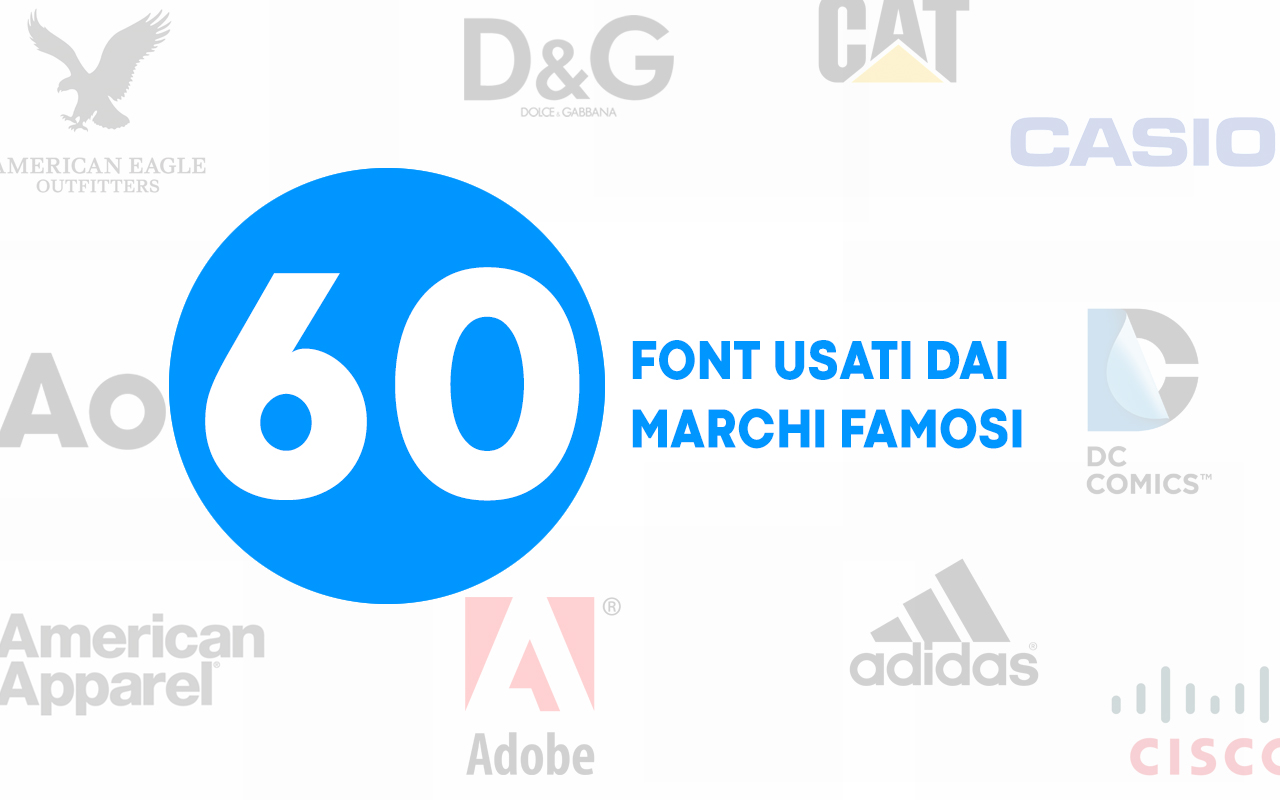
i font utilizzati nei loghi famosi e dove scaricarli
Hai sempre voluto conoscere i nomi dei caratteri utilizzati nei loghi di marchi famosi e conosciutissimi come Adidas, Calvin Klein, FedEx, Gillette, Jaguar, Lufthansa, Omega, Rolls-Royce, Visa, ecc. ? Si? Bene! Abbiamo compilato un elenco in ordine alfabetico di 60 loghi noti con i relativi font usati e i collegamenti al download.
In alcuni casi, i caratteri sono stati modificati dal originale per creare un marchio personalizzato per i singoli marchi oppure sono stati creati ad hoc per il cliente, In questo caso, abbiamo elencato il carattere più vicino possibile che corrisponde al logo.
1. Adidas
Adidas logo font - Avant Garde Gothic Demi
Avant Garde Gothic Demi
2. Adobe
Adobe logo font - Myriad Pro Bold Condensed
Myriad Pro Bold Condensed
3. American Apparel
American Apparel logo font - Helvetica Black
Helvetica Black
4. American Eagle
American Eagle logo font - Garamond / Newburgh
Garamond / Newburgh
5. AOL
AOL logo font - Avenir Next Pro Bold
Avenir Next Pro Bold
6. Aston Martin
Aston Martin logo font - Optima Roman
Optima Roman
7. BBC
BBC logo font- Gill Sans Std
Gill Sans Std
8. Black & Decker
Black & Decker logo font - Avenir Black
Avenir Black
9. Calvin Klein
Calvin Klein logo font - Avant Garde Gothic
Avant Garde Gothic
10. Casio
Casio logo font - Eurostile Ext Black
Eurostile Ext Black
11. Caterpillar
Caterpillar logo font - Helvetica Inserat Roman
Helvetica Inserat Roman
12. Cisco
Cisco logo font - Futura Bold
Futura Bold
13. Dolce & Gabbana
Dolce & Gabbana logo font - Futura Demi Bold
Futura Demi Bold
14. DC Comics
DC Comics logo font - Gotham Bold
Gotham Bold
15. eBay
eBay logo font - Univers 53 Extended
Univers 53 Extended
16. ESPN
ESPN logo font- ESP
ESP
17. Facebook
Facebook logo font - Klavika Bold
Klavika Bold
18. FedEx
FedEx logo font - Futura Bold / Univers 67
Futura Bold / Univers 67
19. Fendi
Fendi logo font - Helvetica Bold
Helvetica Bold
20. Flickr
Flickr logo font - Frutiger Black
Frutiger Black
21. Gillette
Gillette logo font - Futura Extra Black Italic
Futura Extra Black Italic
22. Giorgio Armani
Giorgio Armani logo font - Didot
Didot
23. Groupon
Groupon logo font - Avant Garde Gothic Bold
Avant Garde Gothic Bold
24. HTML 5
HTML 5 logo font - Gotham Ultra
Gotham Ultra
25. IBM
IBM logo font - Men In Blue
Men In Blue
26. iTunes
iTunes logo font - Myriad Bold
Myriad Bold
27. Jaguar
Jaguar logo font - Jaguar JC (customized)
Jaguar JC (customized)
28. Jeep
Jeep logo font - Helvetica Bold
Helvetica Bold
29. LG
LG logo font - Helvetica Black
Helvetica Black
30. LinkedIn
LinkedIn logo font - Myriad Bold
Myriad Bold
31. Lufthansa
Lufthansa logo font - Helvetica Bold
Helvetica Bold
32. Mobil
Mobil logo font - Avant Garde Gothic Bold
Avant Garde Gothic Bold
33. NBA
NBA logo font - Helvetica Condensed Black
Helvetica Condensed Black
34. The New York Times
The New York Times logo font - English Towne
English Towne
35. Nutella
Nutella logo font - Avant Garde Gothic Bold
Avant Garde Gothic Bold
36. Omega
Omega logo font - Futura Medium
Futura Medium
37. Panasonic
Panasonic logo font - Helvetica Black
Helvetica Black
38. PayPal
PayPal logo font - Futura Bold Oblique
Futura Bold Oblique
39. PlayStation 3
PlayStation 3 logo font - PhatBoy Slim
PhatBoy Slim
40. Puma
Puma logo font - My Puma
My Puma
41. Rolls-Royce
Rolls-Royce logo font - Myriad Semi Bold
Myriad Semi Bold
42. Snickers
Snickers logo font - Lunch Time Normal
Lunch Time Normal
43. Spotify
Spotify logo font - LL Circular
LL Circular
44. Standard Chartered
Standard Chartered logo font - Helvetica Neue 55 Roman
Helvetica Neue 55 Roman
45. Subway
Subway logo font - Helvetica Black
Helvetica Black
46. Tag Heuer
Tag Heuer logo font - Gill Sans / Humanist
Gill Sans / Humanist 521
47. Target
Target logo font - Helvetica Neue Bold
Helvetica Neue Bold
48. TGI Friday’s
TGI Friday's logo - Gotham Black
Gotham Black
49. Tommy Hilfiger
Tommy Hilfiger logo font - Gill Sans Regular
Gill Sans Regular
50. Toshiba
Toshiba logo font - Eurostile Black
Eurostile Black
51. Toyota
Toyota logo font - Avenir 95 Black
Avenir 95 Black
52. Under Armour
Under Armour logo font - Eurostile Black Extended
Eurostile Black Extended
53. UNICEF
UNICEF logo font - Univers Light
Univers Light
54. USA Today
USA Today logo font - Futura Bold
Futura Bold
55. Visa
Visa logo font - Myriad Black Italic
Myriad Black Italic
56. Vogue
Vogue logo font - Didot
Didot
57. Walmart
Walmart logo font - Myriad Pro Bold
Myriad Pro Bold
58. Walt Disney
Walt Disney logo font - Walt Disney Script
Walt Disney Script
59. WhatsApp
WhatsApp logo font - Helvetica Neue 75 Bold
Helvetica Neue 75 Bold
60. YouTube
YouTube logo font - Trade Gothic Bold Condensed No. 20
Trade Gothic Bold Condensed No. 20